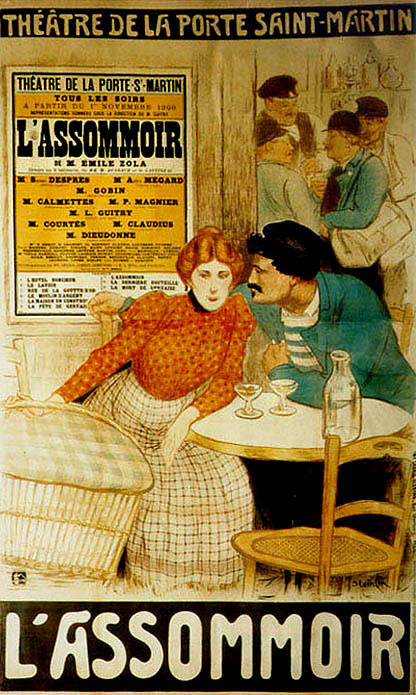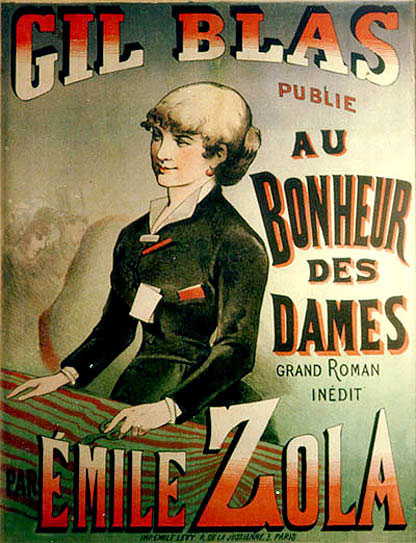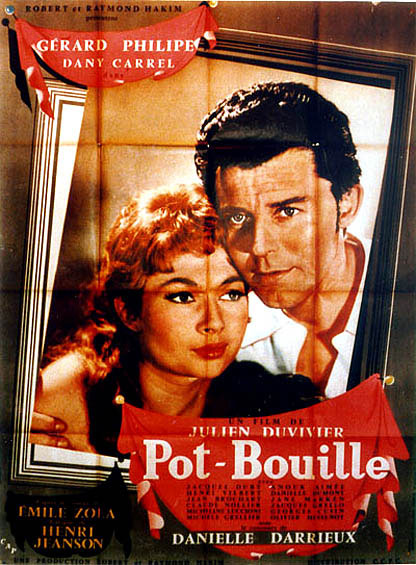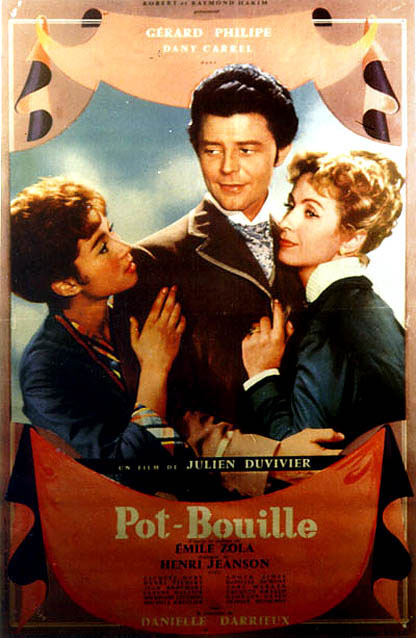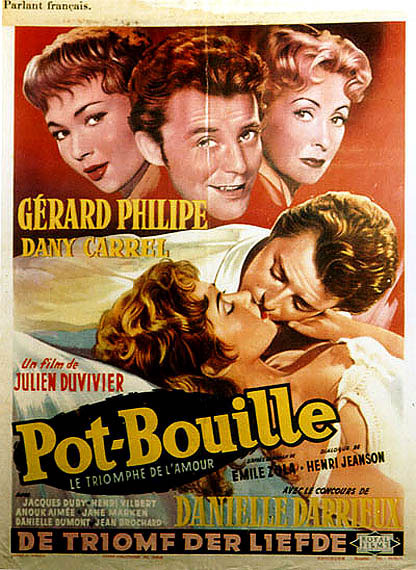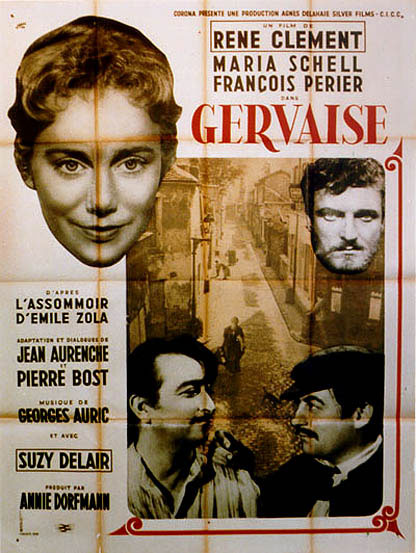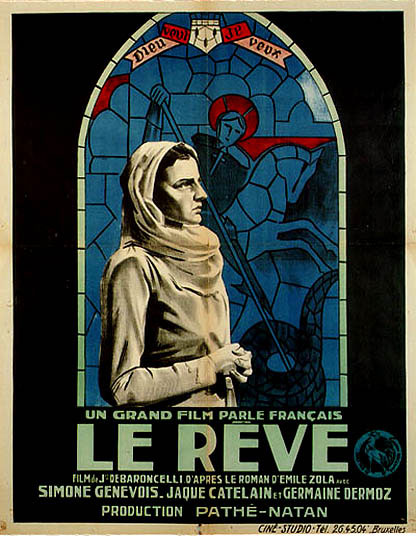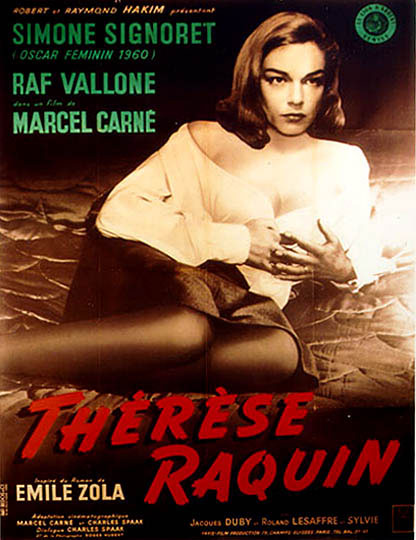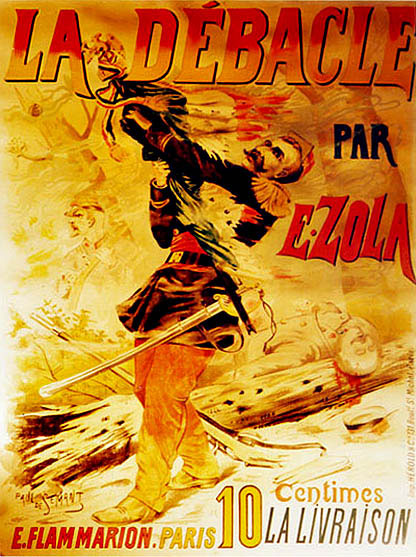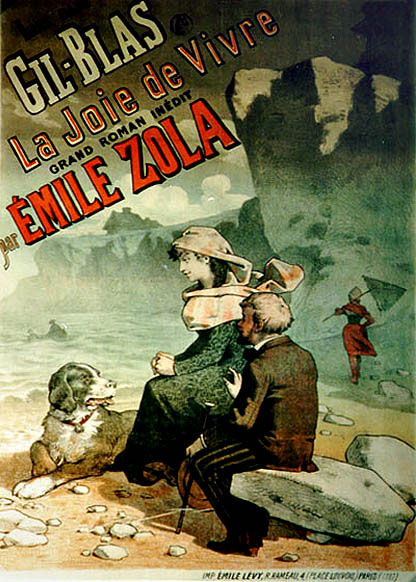
Zola et la Typographie | le lettrage comme acteur militant
Via la Société Emile Zola, voici une série d’affiches des œuvres théâtrales, littéraires et cinématographiques issues de l’œuvre d’Emile Zola. Tout le monde se souvient bien entendu de son célèbre J’Accuse parue dans le Figaro du 13 janvier 1898. Mais si vous voulez revivre cette affaire Dreyfus, rien de tel que de vous replonger dans le timeline édité par la Emile Zola Society. Je me suis plus particulièrement attaché à vous montrer ces quelques affiches de l’époque qui témoignent de plusieurs choses.
Typographie Foisonnante:
Chacune des affiches laisse paraître l’utilisation de nombreux caractères sauf peut-être celle de NANA ci-dessous mais il s’agit là certainement d’un teasing et non d’une affiche complète. Regardez Gervaise ou Le Rêve ou encore Pot-Bouille, ce sont de véritables catalogues de caractères de l’époque. Bien entendu chacun des titres était dessiné et peint à la main. Point de machines à composer ni même de Letraset (lettres transferts) à l’époque. Nombre des créateurs contemporains s’inspirent encore de ces affiches pour créer de nouveaux alphabets. Et je ne prendrai que la ligne «DE TRIOMF DER LIEFDE» dans Pot-Bouille, pour y voir les prémices d’un caractère de Zuzana Licko. Le mélange des styles: il est caractéristique et d’une époque et du graphisme français en particulier. Le Bauhaus n’a pas touché l’industrie cinématographique du pays de Voltaire. On le récuse même pour s’envoler vers un certain lyrisme «à la française» où l’on mélange tout et son contraire. Mais il faut aussi savoir qu’en ces temps reculés, le graphiste de film était plus souvent le peintre en lettre qu’un affichiste comme Cassandre. Autant dire que la structure graphique de ces posters n’obéissait pas à une école graphique d’avant garde mais à une expressivité lyrique bien encrée dans les journaux illustrés des années 30-50.
Expressivité graphique:
Chaque ligne, chaque mot typographié par le peintre en lettre devait hurler un message, un sens. Et dans le cas de Zola c’était d’autant plus facile que l’œuvre est dédié à dénoncer la condition in-humaine faite aux classes laborieuses. Que ce soit pour la Débacle, ou au Bonheur des Dames ou encore l’assomoir sans parler bien entendu du plus célèbre des romans-sociaux, Germinal, l’artiste peintre en lettre se sert de la typographie pour engranger la force des messages. On n’ose imaginer que seraient ces affiches mises entre les mains d’Experimental Jetset. Uniformité de l’Helvetica. Neutralité neutralisant la poésie des signes typographiques neutralisant par voie de conséquence la sémantique forte de ces visuels. Seule une affiche cependant cède à la tendance russe du graphisme constructiviste, celle de l’Argent qui correspond vraiment à un thème et un traitement typographique de l’actualité des années 30.
La couleur et les manuaires, amplificateurs de messages:
Le Rouge et le Noir sont les couleurs fétiches de ces affiches, agrémentées du jaune Pantone 123 et plus foncés, ainsi que d’une série de complémentaires lorsque dans «La joie de Vivre» l’affichiste mélange le vert et le rouge. L’utilisation prolixe de caractères brushes augmente la force des titres par leur proximité du spectateur qu’ils prennent à témoin des drames humains. Mais on pourrait analyser affiche par affiche, titre par titre et vous en laisse toute liberté dans vos commentaires assidus.
« chacun des titres était dessiné et peint à la main »
Avec un pochoir ou à la main levée ? Dans La revue illustrée on a pas l’impression que c’est fait à la main.